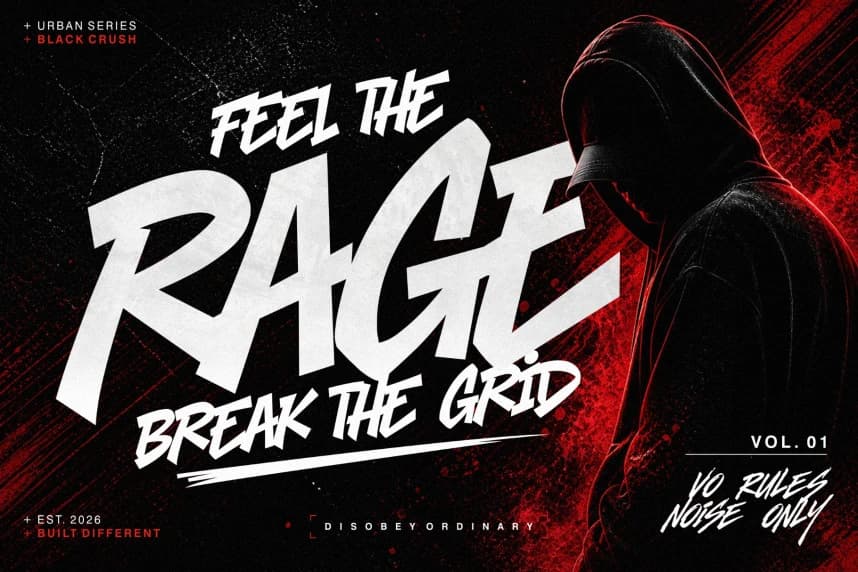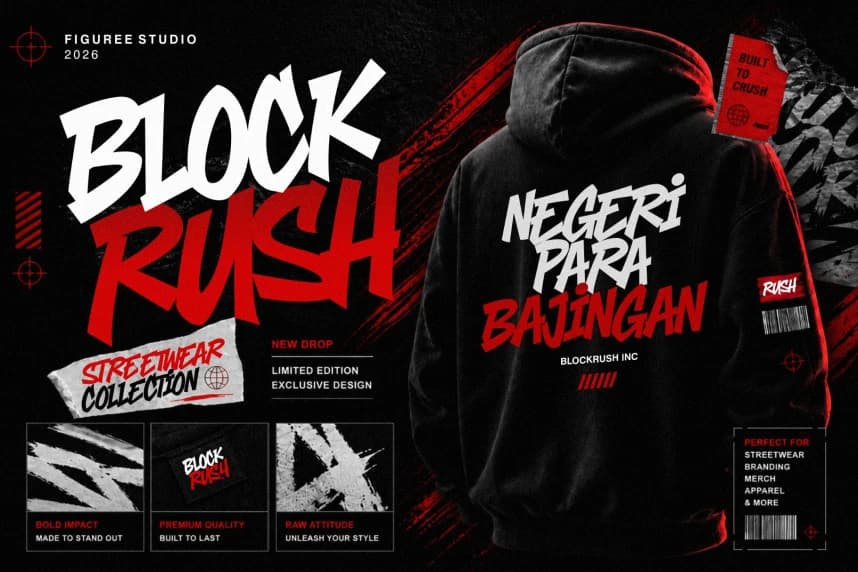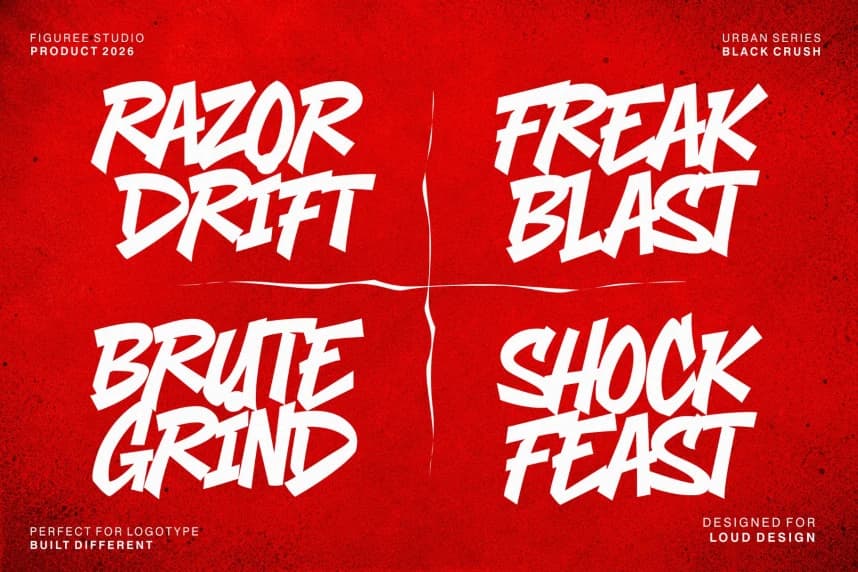
Black Crush Font – Aggressive Urban Font, mükemmel bir seçimdir. Güçlü geometrik şekiller, keskin kenarlar ve ifade gücü yüksek kentsel estetiklerle tasarlanmıştır; bu yazı tipi, çalışmalarını yüksek sesle ve kendinden emin bir şekilde öne çıkarmak isteyen tasarımcılar için üretilmiştir.
Black Crush Font – Aggressive Urban Font mükemmel bir seçimdir. Güçlü geometrik şekiller, keskin kenarlar ve ifadeli kentsel estetiklerle tasarlanmış bu yazı tipi, çalışmalarının yüksek sesle ve kendinden emin bir şekilde öne çıkmasını isteyen tasarımcılar için üretilmiştir.